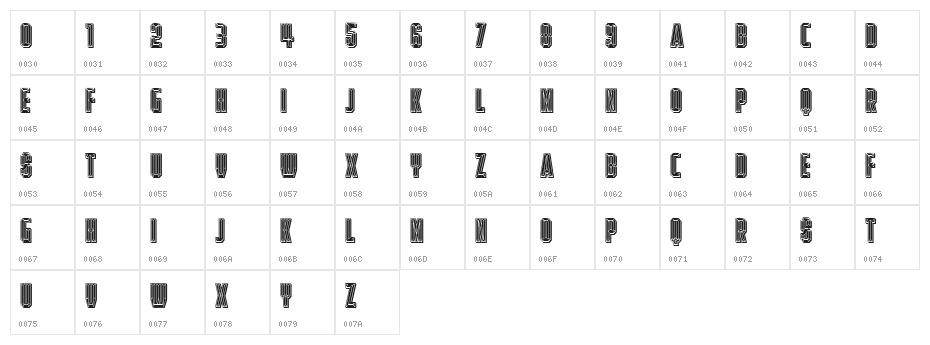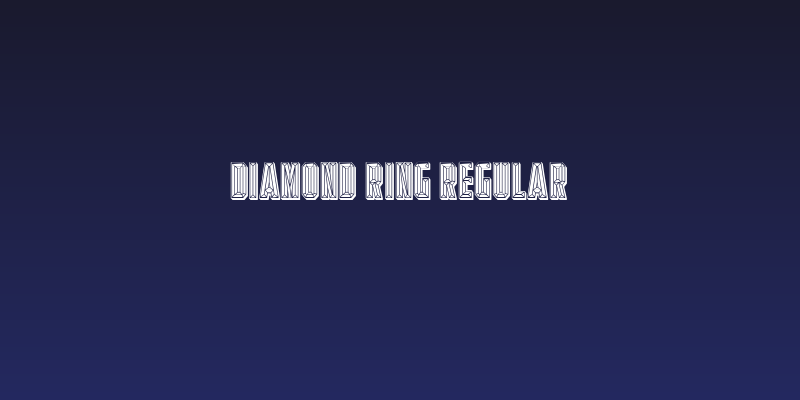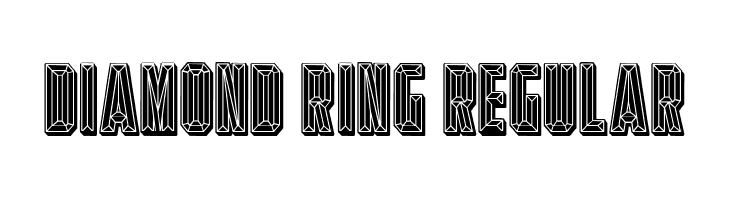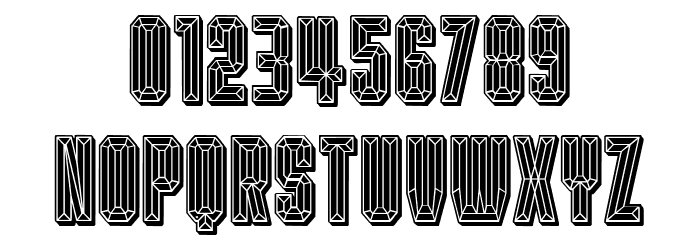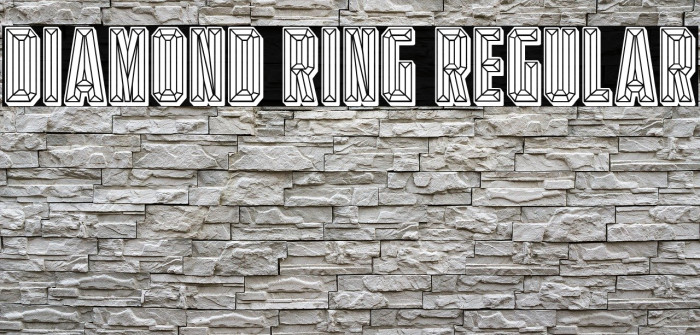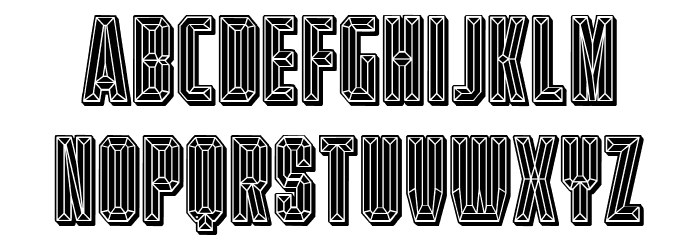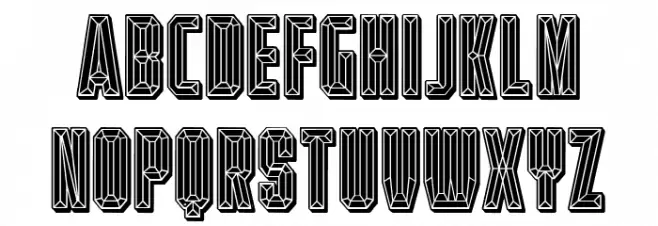
Diamond Ring Regular Font
| Família da fonte | Diamond Ring |
| Projetos propostos | Ideal for luxury branding, event invitations, posters, and any design requiring a touch of elegance and sophistication. |